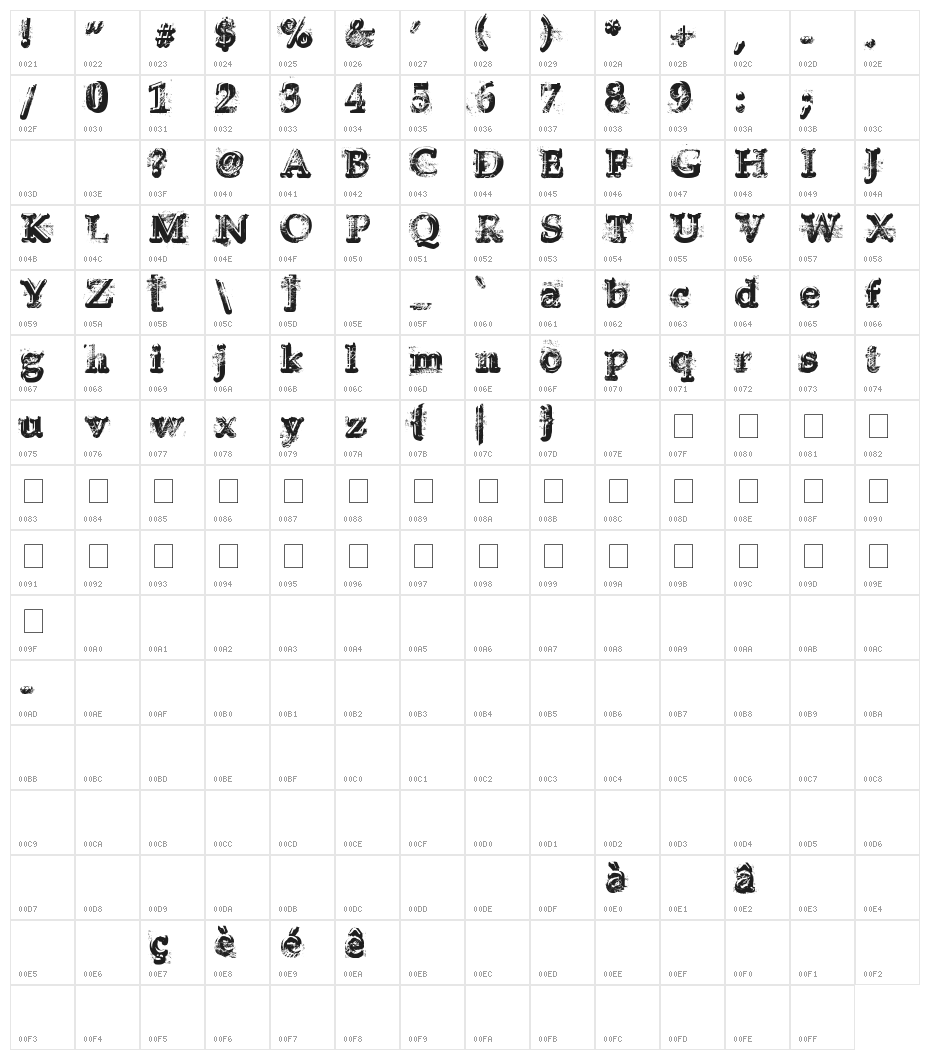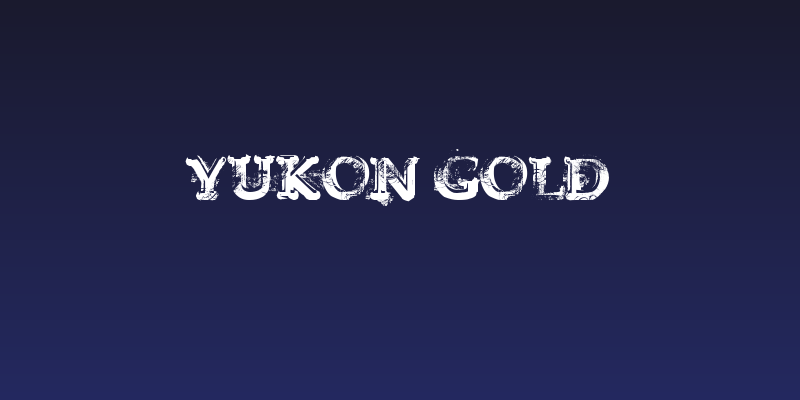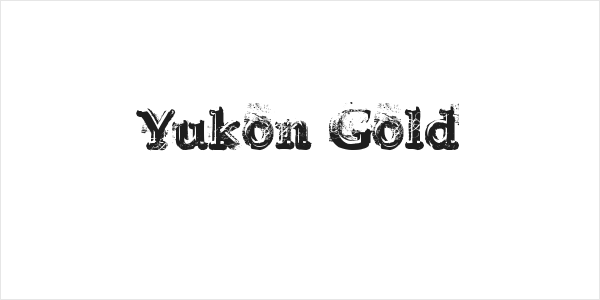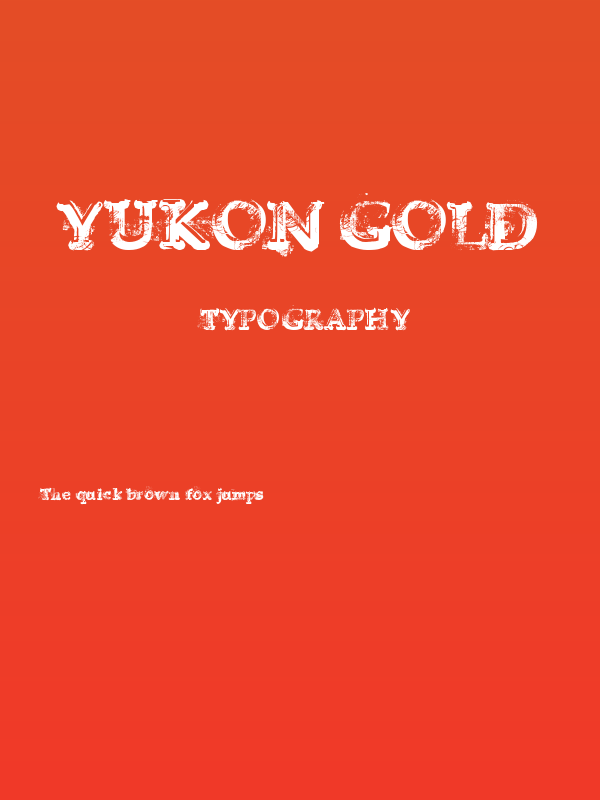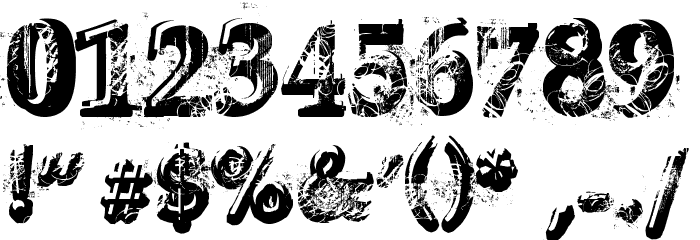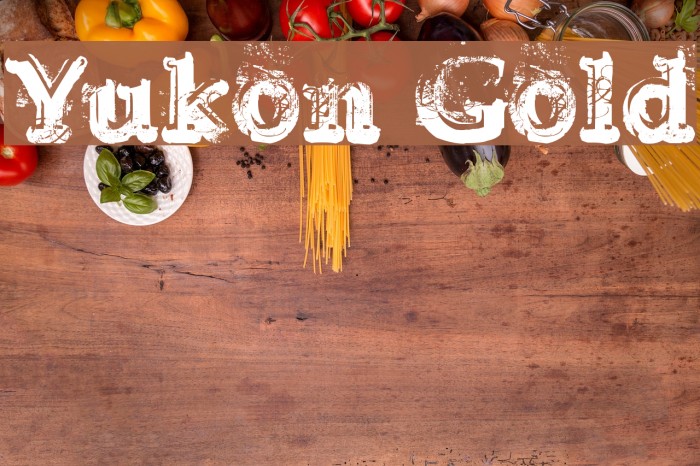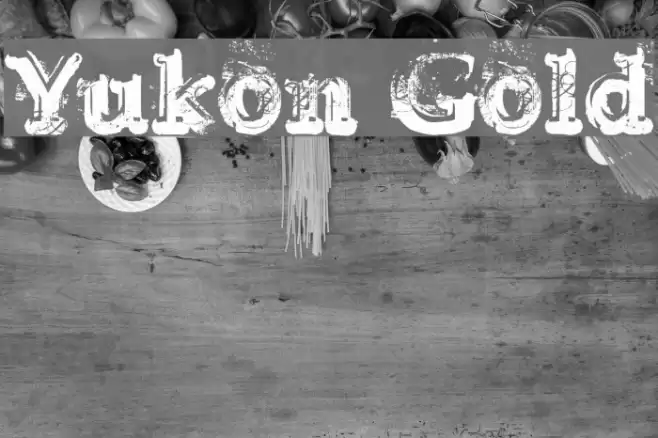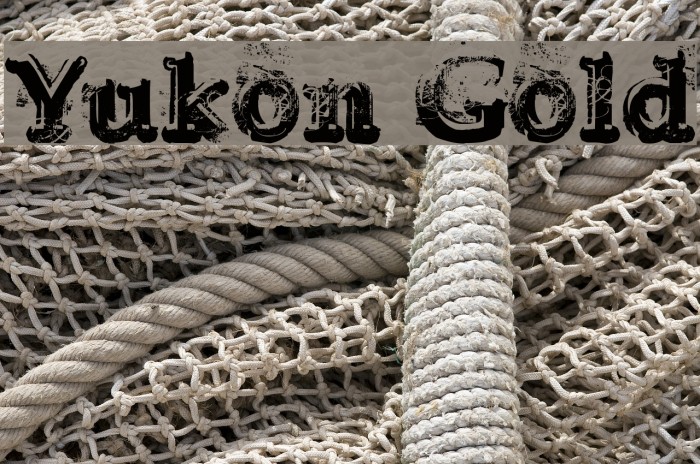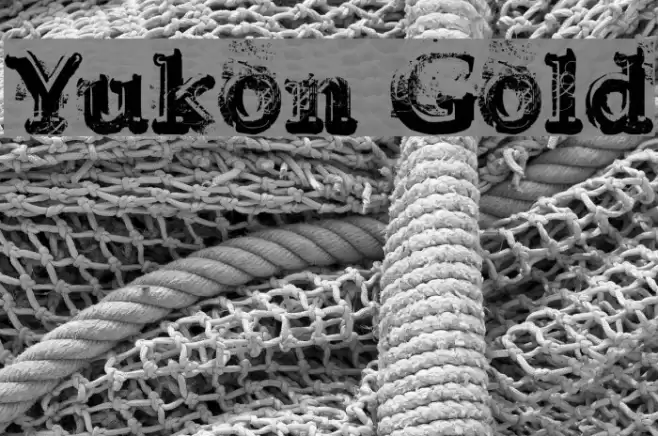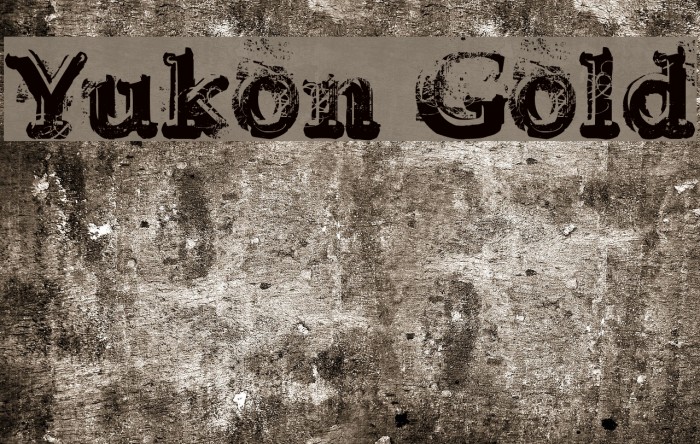
Yukon Gold Font
✎ Distorted Eroded
| Proiecte propuse | Ideal for vintage-themed posters, album covers, branding for rustic or artisanal products, and any design needing a bold, textured look. |